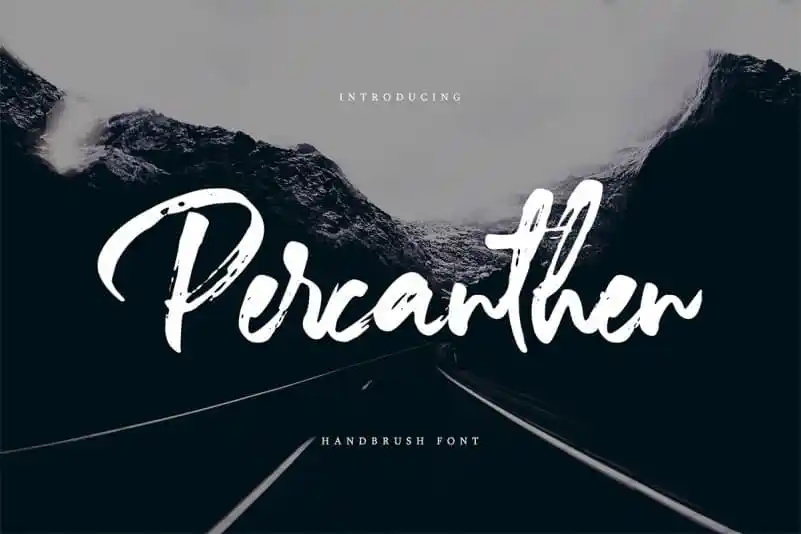
Percanthen Brush Font – Download Grátis
A fonte “Percanthen Brush” é uma atraente escolha para aqueles que desejam dar um toque moderno e elegante aos seus projetos digitais, seja em redes sociais, logotipos ou até mesmo no design de embalagens. Esta fonte foi criada pelo designer Vztype utilizando o estilo das canetas. Com sua gráfica fluida e sofisticada, ela é perfeita para dar um ar alegre e único às suas criações digitais. Ideal tanto para projetos branding quanto para aplicações em redes sociais ou anúncios promocionais, a fonte “Percanthen Brush” oferece uma maneira única de incorporar estilo na sua obra. Além disso, ela também se destaca como uma opção perfeita para as t-shirts customizadas, produtos embalados e até mesmo os cartões de convite ou papelão do seu negócio. Adicionar esta font a seus projetos é não apenas adicionar um toque único ao seu design digital, mas também fazer com que sua marca seja lembrada de uma maneira especial. Sem dúvida, ela traz um brilho à sua produção e certamente fará seu público se destacar em meio às muitas outras opções disponíveis na internet. Combinado a seu trabalho artístico ou comercial, “Percanthen Brush” oferece uma maneira criativa de tornar as suas obras ainda mais memoráveis. É um excelente recurso para designers, artistas digitais e qualquer pessoa que esteja buscando dar vida ao design digital, sem perder o toque pessoal.